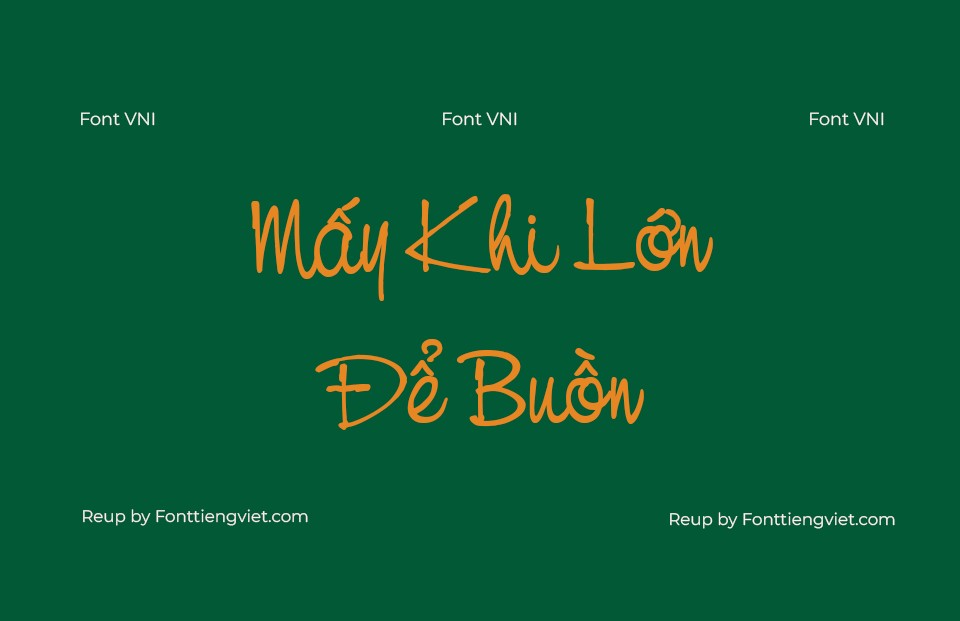
Trong thế giới của thiết kế đồ họa và in ấn, việc lựa chọn Font Chữ phù hợp đóng vai trò then chốt trong việc truyền tải thông điệp và tạo ấn tượng mạnh mẽ. Đối với những ai yêu thích vẻ đẹp truyền thống và nét chữ mềm mại, bay bổng, Font Việt hoá VNI ThanhCao chính là một lựa chọn không thể bỏ qua. Đây là một trong những font chữ thư pháp được cộng đồng thiết kế, đặc biệt là các bạn học sinh sinh viên hay người làm công việc sáng tạo nội dung, săn đón nhiều nhất. Sự kết hợp giữa tính thẩm mỹ cao và khả năng tương thích tiếng Việt hoàn hảo đã biến VNI ThanhCao thành một “ngôi sao” trong bộ sưu tập font chữ cá nhân của nhiều người. Hãy cùng khám phá chi tiết về đặc điểm, ứng dụng và cách tải font chữ tuyệt vời này.
Giới thiệu chi tiết về Font Việt hoá VNI ThanhCao và nguồn gốc
Font Việt hoá VNI ThanhCao thuộc nhóm font thư pháp (script/calligraphy), nổi bật với những nét chữ uốn lượn, bay bổng nhưng vẫn giữ được sự rõ ràng, dễ đọc. Khác với các font chữ hiện đại, VNI ThanhCao mang đến cảm giác hoài cổ, tinh tế, rất phù hợp cho các thiết kế mang tính nghệ thuật, truyền thống hoặc cần sự trang trọng. Nguồn gốc của font này nằm trong bộ mã VNI (Vietnamese National Institute), một hệ thống bảng mã phổ biến trước đây, đặc biệt được ưa chuộng trong các phần mềm văn phòng cũ và in ấn chuyên nghiệp tại Việt Nam. Dù ngày nay Unicode đã trở nên phổ biến, các phiên bản Việt hoá chuẩn VNI vẫn được duy trì và phát triển để đáp ứng nhu cầu sử dụng font chữ đa dạng, đặc biệt là các font thư pháp độc đáo mà chỉ hệ thống VNI mới có.
Sự khác biệt giữa VNI ThanhCao và các font thư pháp khác
Nhiều font thư pháp thường quá cầu kỳ, khiến chữ bị rối và khó đọc khi áp dụng vào các đoạn văn dài. Tuy nhiên, VNI ThanhCao lại tìm được sự cân bằng hoàn hảo. Các nét thanh, nét đậm được phân bố hợp lý, tạo nên tổng thể hài hòa. Điểm đặc biệt của font này là cách xử lý các dấu tiếng Việt, đảm bảo dấu câu và dấu thanh không bị chồng chéo hay làm mất đi tính thẩm mỹ chung của chữ viết. Điều này cực kỳ quan trọng đối với các bạn học sinh hay giáo viên khi cần tạo ra các tài liệu học tập, bìa sách, hay thậm chí là thiệp chúc mừng tốt nghiệp.
Font chữ này thường được sử dụng trong các ngữ cảnh yêu cầu tính nghệ thuật cao như: thiết kế thiệp cưới, poster phim lịch sử, bìa tiểu thuyết, hay các ấn phẩm kỷ niệm về trường học, các sự kiện quan trọng như lễ bế giảng và các kỳ thi cuối cấp.
Ứng dụng đa dạng của Font ThanhCao trong học tập và thiết kế
Không chỉ giới hạn trong lĩnh vực thiết kế đồ họa chuyên nghiệp, Font Việt hoá ThanhCao còn có nhiều ứng dụng hữu ích trong đời sống học tập và công việc của học sinh, sinh viên và giáo viên. Dưới đây là một số ví dụ điển hình:
- Thiết kế bài giảng và tài liệu học tập: Giáo viên có thể sử dụng font này để thiết kế các tiêu đề bài giảng, slide PowerPoint, hoặc các tài liệu quảng bá hoạt động của trường học, tạo sự thu hút và trang trọng.
- Sáng tạo nội dung cho học sinh cấp 3: Các bạn học sinh đang chuẩn bị cho kỳ thi tốt nghiệp trung học phổ thông hoặc các cuộc thi sáng tạo nội dung có thể dùng VNI ThanhCao để thiết kế bìa kỷ yếu, báo tường, hoặc các dự án nghệ thuật cá nhân, giúp sản phẩm của mình nổi bật hơn.
- Thiết kế thư pháp và câu đối: Đối với những người yêu thích văn hóa truyền thống, VNI ThanhCao là công cụ không thể thiếu để viết các câu đối, thiệp mừng dịp lễ Tết, hay các tác phẩm thư pháp hiện đại.
- Branding cá nhân và doanh nghiệp nhỏ: Font này mang lại cảm giác cao cấp và nghệ thuật, phù hợp cho các thương hiệu cá nhân hoặc các cửa hàng kinh doanh sản phẩm thủ công, quà tặng.
Sự tiện lợi và tính thẩm mỹ vượt trội đã làm cho VNI ThanhCao trở thành một tài sản quý giá cho bất kỳ ai hoạt động trong lĩnh vực sáng tạo. Dù bạn là một học sinh cấp 3 đang tìm kiếm font chữ độc đáo cho bài dự thi hay một nhà thiết kế chuyên nghiệp, font này chắc chắn sẽ làm phong phú thêm kho tàng tài nguyên của bạn.
Tóm lại, Font Việt hoá VNI ThanhCao không chỉ là một phông chữ đơn thuần mà còn là biểu tượng của sự tinh tế và nét đẹp thư pháp truyền thống Việt Nam. Với những ưu điểm vượt trội về mặt thẩm mỹ và khả năng tương thích tiếng Việt chuẩn VNI, font này xứng đáng có mặt trong bộ sưu tập của mọi người. Dù bạn đang chuẩn bị cho các kỳ thi quan trọng, thiết kế một tấm thiệp chúc mừng, hay chỉ đơn giản là tìm kiếm một Font Chữ đẹp để làm mới giao diện tài liệu của mình, VNI ThanhCao sẽ mang lại kết quả ấn tượng. Hãy tải ngay và trải nghiệm sự khác biệt mà font thư pháp độc đáo này mang lại!